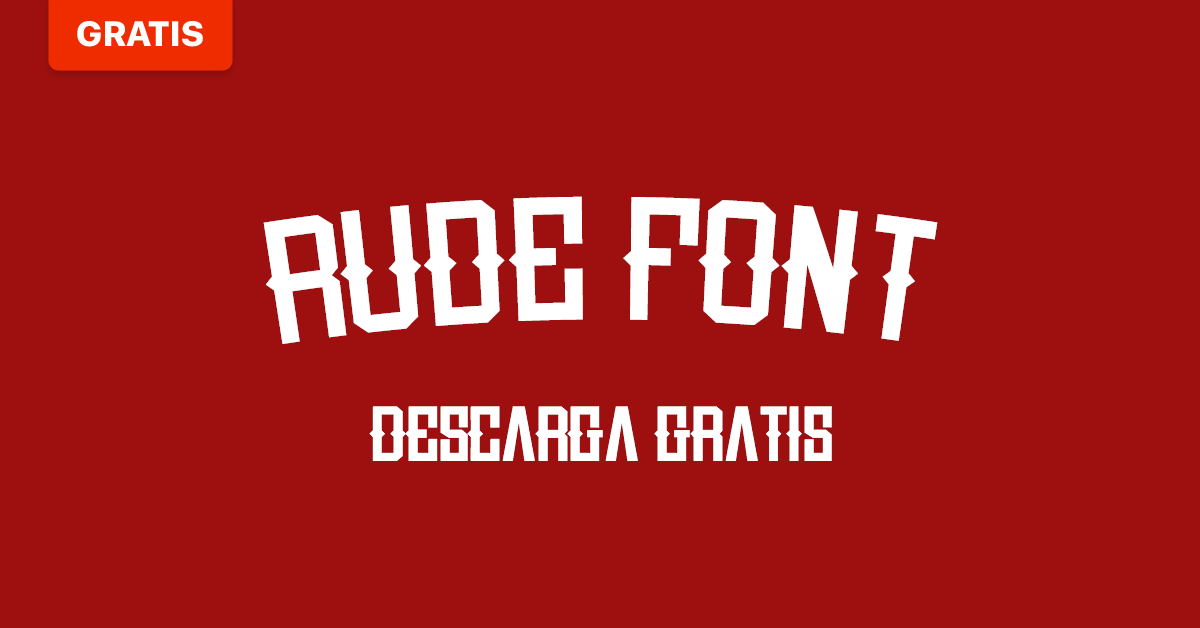
Descarga gratis la tipografía Rude, de Miguel Nieto
El diseñador gráfico Miguel Nieto comparte con Domestika la tipografía 'Rude Font' para que la descargues gratis.
El diseño de 'Rude Font' surgió, para Miguel Nieto (@miguelnieto), como fruto de la necesidad de tener una tipografía inspirada en las publicidades de principios del siglo pasado. Con esto en mente, el diseñador ideó una adaptación de las clásicas fuentes publicitarias creando una adaptación más moderna y con un aire más urbano. Fue así como fueron tomando forma los glifos de esta tipografía que ahora comparte con Domestika de manera completamente gratuita y que puedes descargarte al final de este post.
La fuente fue diseñada por Nieto en Adobe Illustrator y FontLab y él mismo cuenta que tuvo claro desde el primer momento cómo quería que fuese y las satisfacciones no se han quedado en un proyecto personal, sino que han llegado mucho más lejos:
"Un día, andando por la calle, me fijé en la camiseta que llevaba un chico que iba caminando delante de mí y en la misma vi que habían usado la tipografía Rude. Me acerqué a preguntarle dónde la había comprado y me sorprendió que fuese el nombre de una importante multinacional textil, con los que por cierto, me puse en contacto. Esto supuso una gran alegría para mí ya que, cuando haces un proyecto personal, no esperas que tenga dicho alcance."